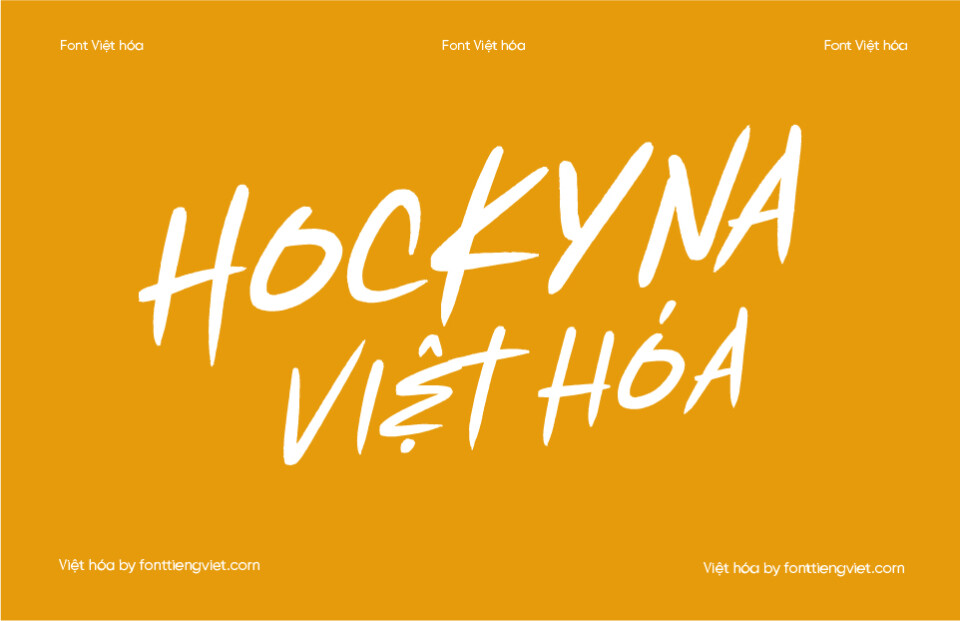
Tải Ngay Font Việt hóa 1FTV VIP Hockyna Cho Thiết Kế Giáo Dục Và Học Đường
Giới thiệu về bộ Font Việt hóa 1FTV VIP Hockyna
Trong môi trường học đường hiện đại, việc sử dụng các mẫu Font Chữ đẹp mắt đóng vai trò quan trọng trong việc truyền tải thông tin. Font Việt hóa 1FTV VIP Hockyna là một lựa chọn tuyệt vời dành riêng cho các thầy cô giáo và học sinh trong việc thiết kế bài giảng. Đây là bộ font mang phong cách hiện đại, thanh lịch nhưng vẫn giữ được nét gần gũi, phù hợp với tinh thần năng động của lứa tuổi học trò.
Đặc điểm nổi bật của Font Việt hóa 1FTV VIP Hockyna
Bộ phông chữ này được tinh chỉnh kỹ lưỡng với đầy đủ dấu tiếng Việt, giúp người dùng không còn lo lắng về lỗi hiển thị khi soạn thảo văn bản. Cấu trúc chữ rõ ràng, dễ đọc trên cả màn hình máy tính và bản in, giúp các bài thuyết trình hay tờ rơi sự kiện trường học trở nên chuyên nghiệp hơn bao giờ hết. Sự linh hoạt của nó cho phép áp dụng vào nhiều mục đích khác nhau từ làm tiêu đề đến nội dung chi tiết.
Cách ứng dụng Font Việt hóa 1FTV VIP Hockyna trong học tập
Các em học sinh có thể sử dụng bộ chữ này để trang trí báo tường, làm thiệp chúc mừng hoặc tạo ra những bản kế hoạch học tập cá nhân sinh động. Đối với giáo viên, đây là công cụ hữu hiệu để làm mới giáo án điện tử, tạo sự hứng thú cho học sinh trong mỗi tiết học. Tính thẩm mỹ của phông chữ giúp thị giác người xem thoải mái, từ đó nâng cao hiệu quả tiếp nhận kiến thức và ghi nhớ thông tin lâu hơn.
Kết luận về bộ phông chữ dành cho trường học